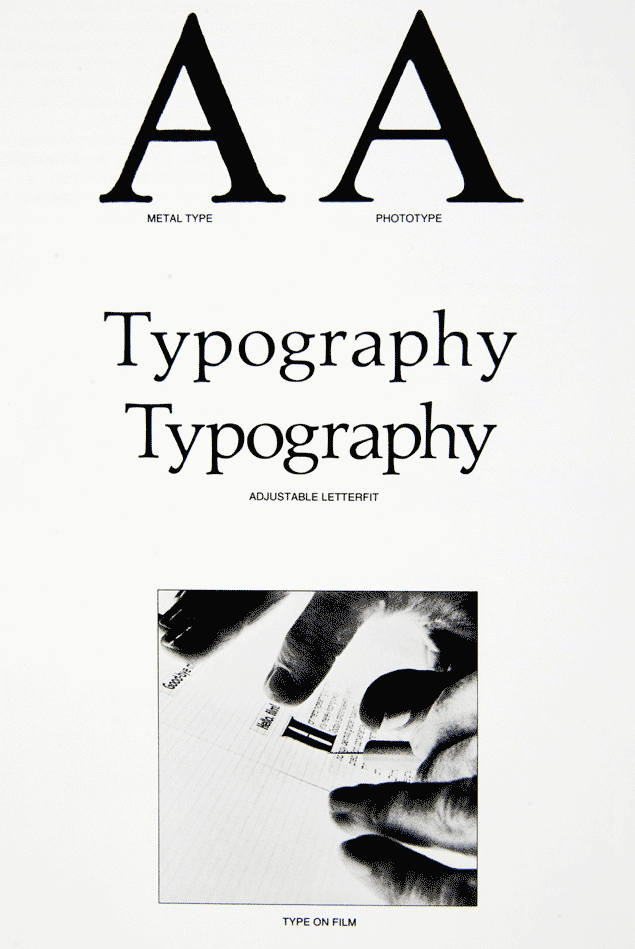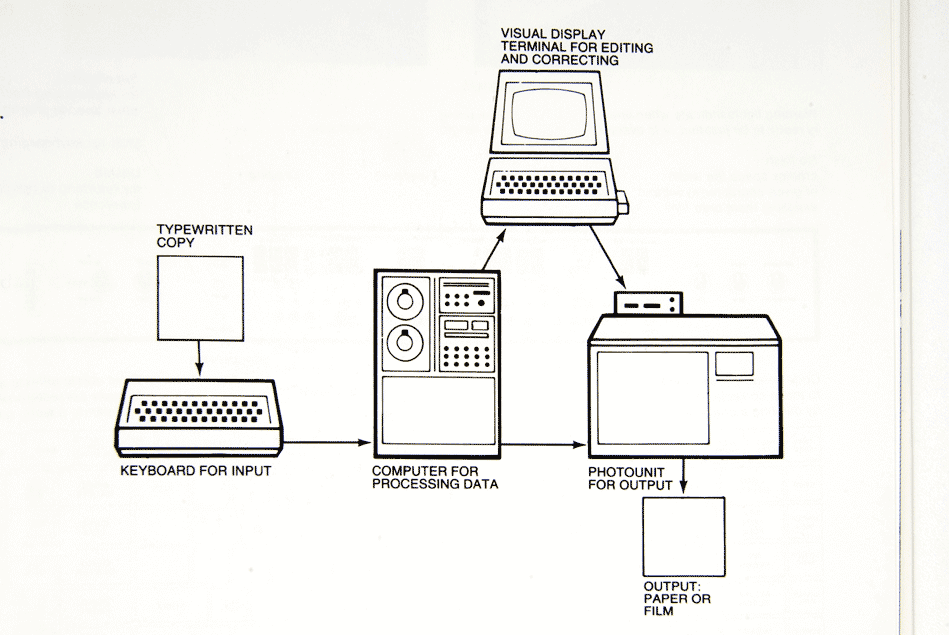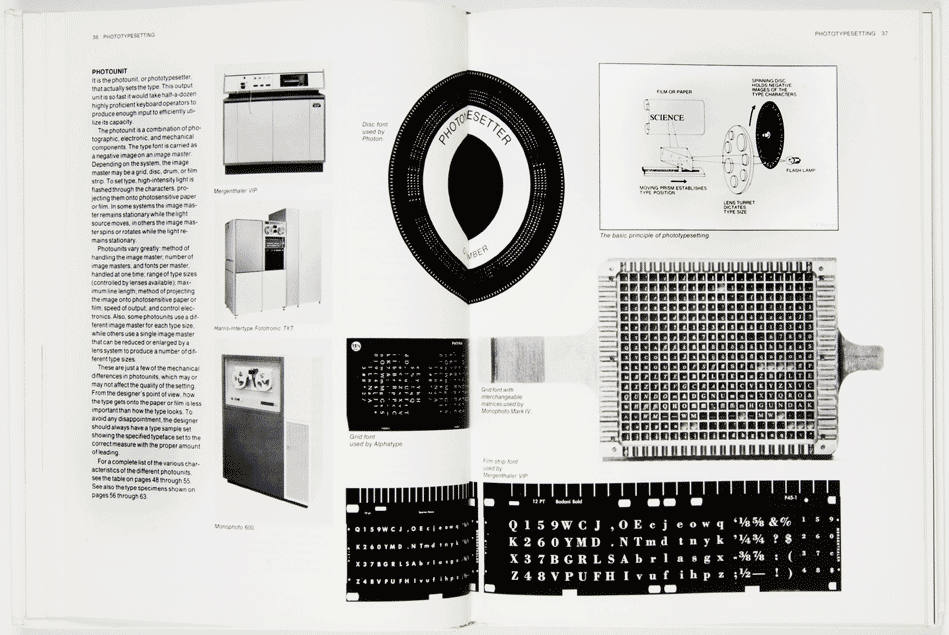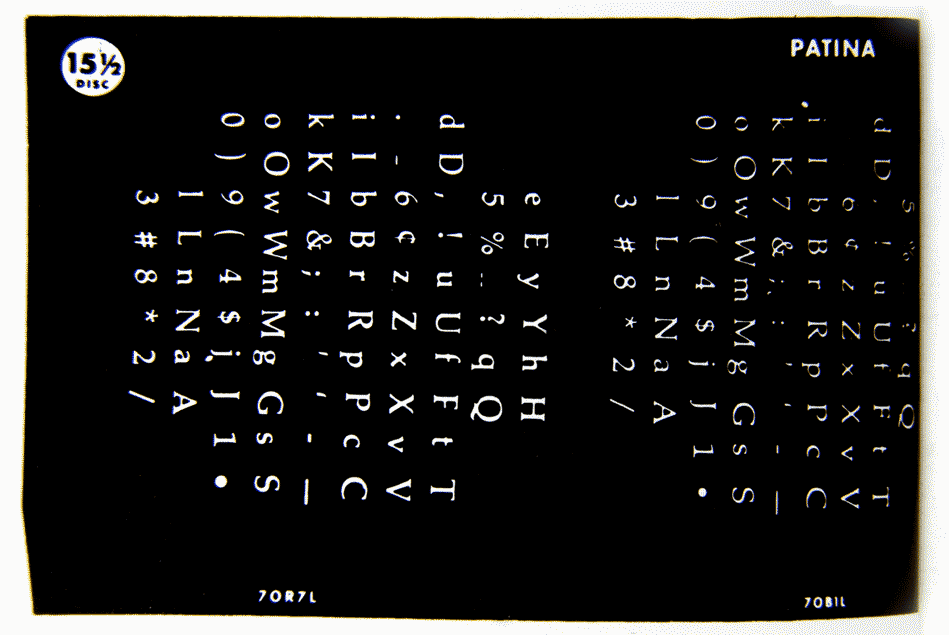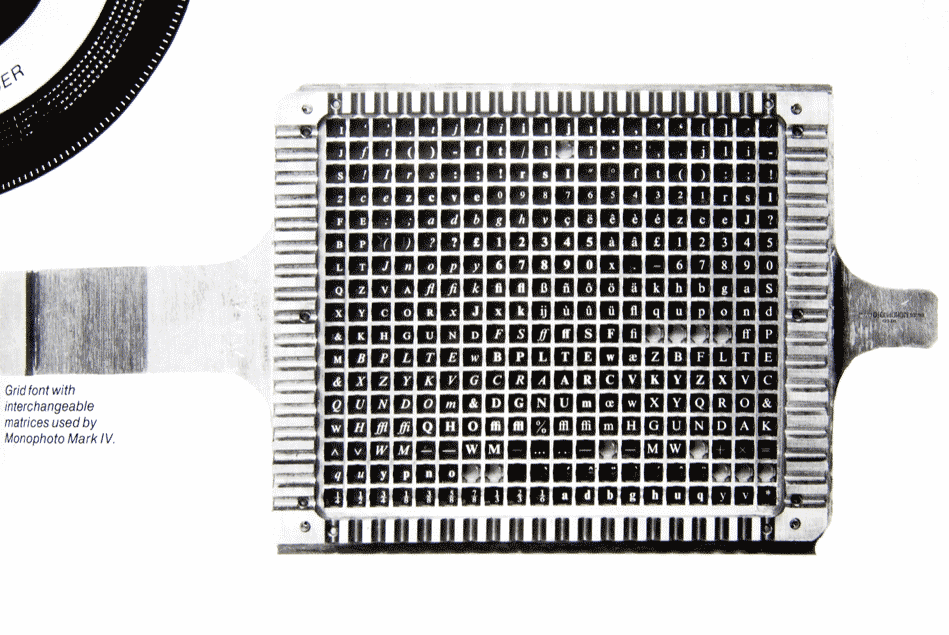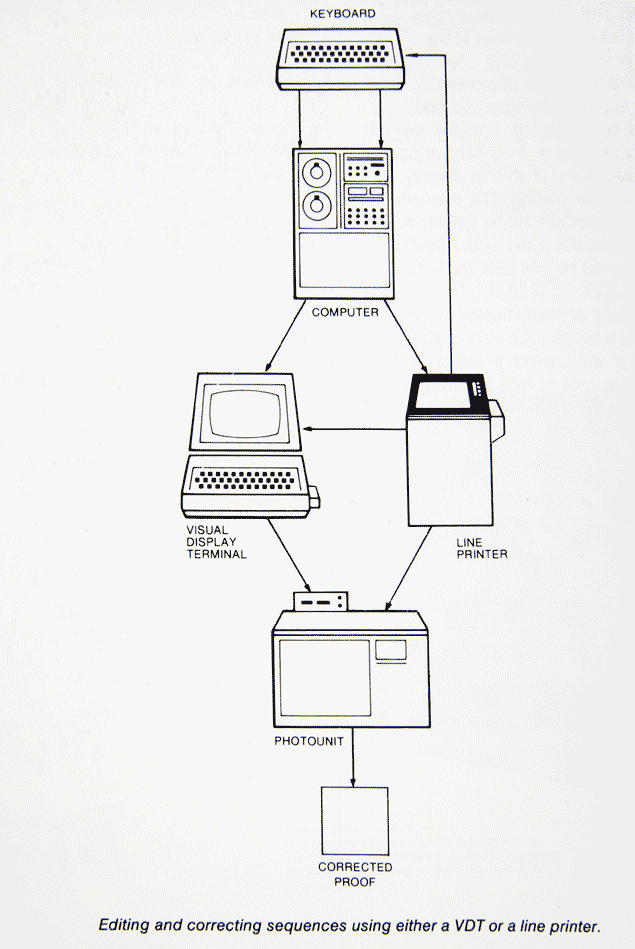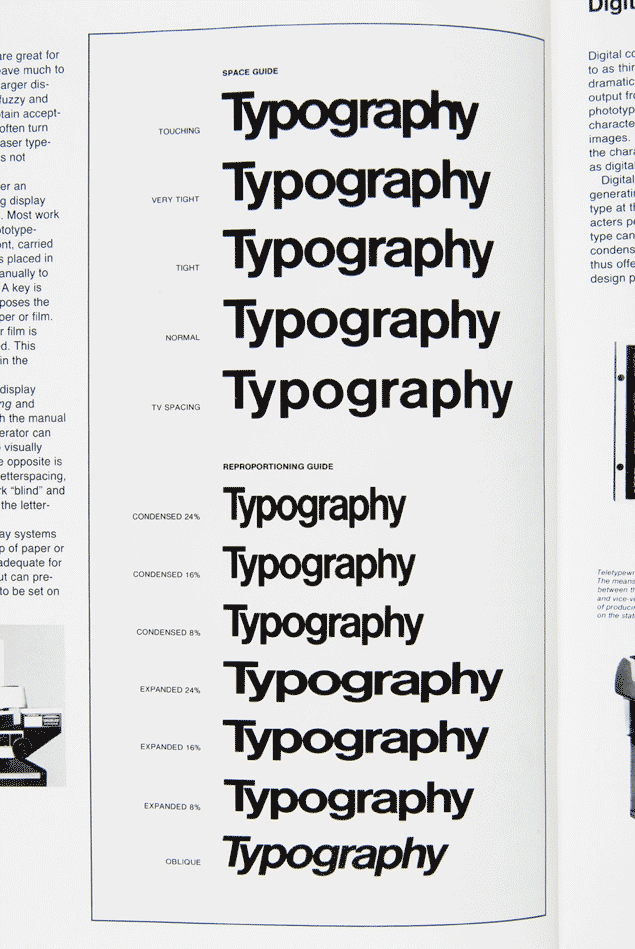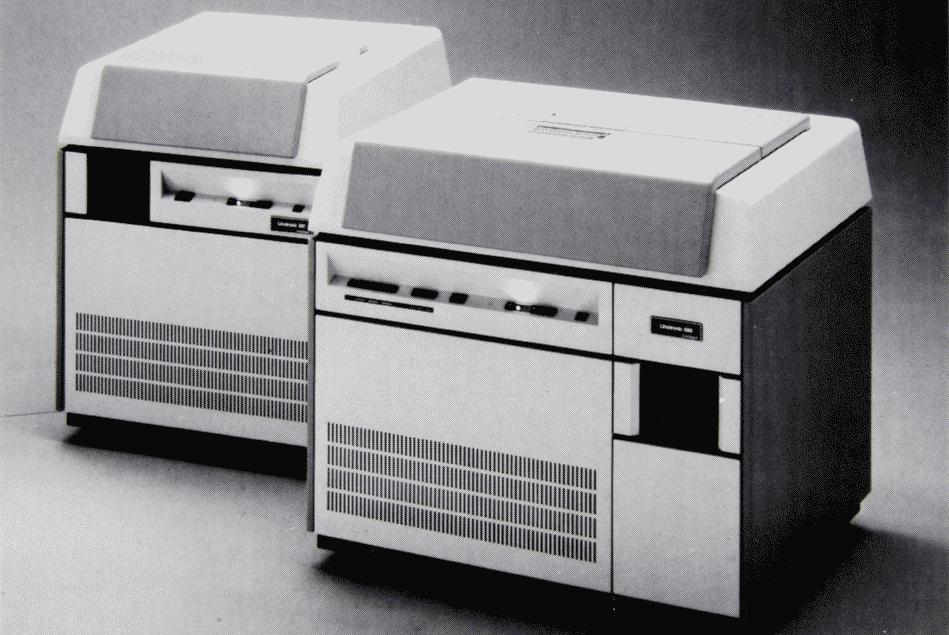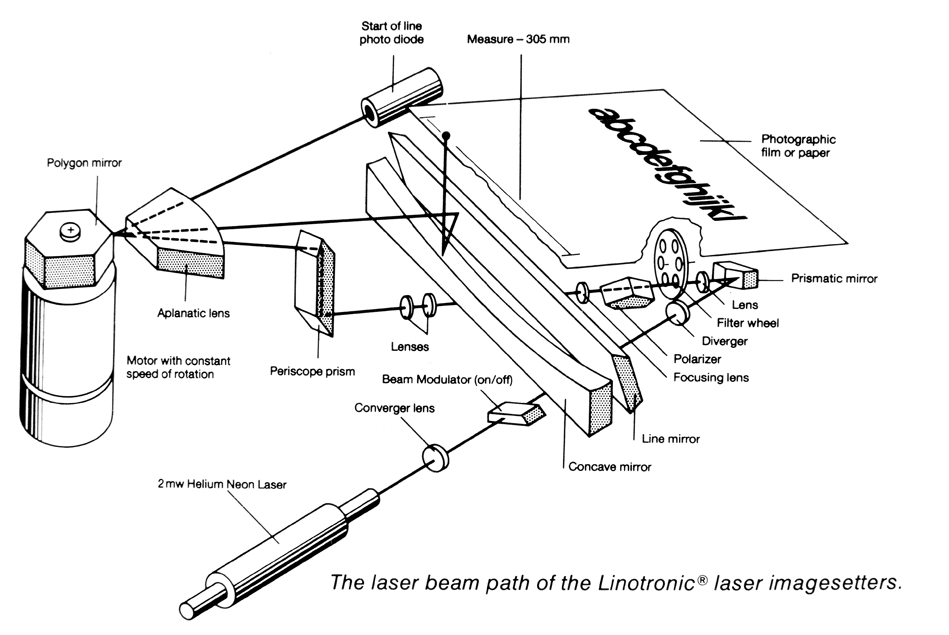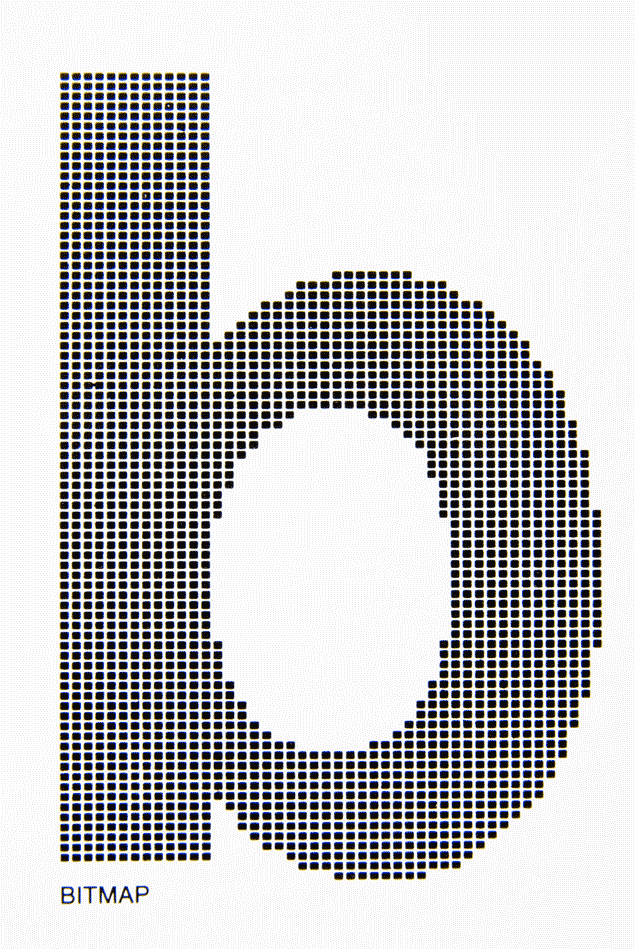
Production graphique pour les graphistes et designers | La typographie: l’ère de la photocomposition
Sous le numéro ISBN 0-8230-4416-5, l’éditeur Watson Guptill Publications a réédité l’ouvrage de James Craig en 1990. Il s’agit de la seconde édition d’une somme qui fut mis en librairie la première fois en 1974. Cet ouvrage n’a pris que quelques rides inhérents aux évolutions technologiques des quinze dernières années. Autrement dit il m’appartient d’y ajouter prochainement deux-trois reportages photo réalisés dans un atelier «pre-press» des plus modernes ainsi que dans une imprimerie qui travaille comme la plupart en DTP, direct to plate, en flux pdf de production.
IBM Selectric MT/ST (en haut) et Smith Corona PWP100 personnal word processor
il faut cliquer sur l’image pour constater la différence de qualité entre une lettre «frappé» par le plomb et une lettre «insolée» par une photocomposeuse.
montage sur film d’une lettrine photographiée avec du texte photocomposée. Le montage effectuée, il est ensuite contretypé en négatif avec un filmprocess orthochromatique (insensible à la lumière rouge) et tirée en positif après retouches pour être montée dans la forme définitive qui servira à la copie de la plaque offset.
Louis Moyroud au centre et René Higonnet à droite, les inventeurs de la Lumitype en 1949 (première photocomposeuse au monde) chez Deberny et Peignot qui durent vendre leurs brevets à l’américain Photon n’ayant pas réussi à interresser les financiers en France. L’ancètre des machines Compugraphic. C’est précisément la Lumitype qui permit à Adrien Frutiger en complicité avec Ladislas Mandel de réaliser la série incroyable des Univers. Les deux ingénieurs, spécialisés dans la transmission et les relais électromagnétiques travaillaient dans les télécomunications de l’époque.
une photocomposeuse également. L’intertype photosetter, où vous retrouvez la structure de fonctionnement des linotypes sauf que les matrices cette fois ne servent plus à couler les lettres en plomb mais à insoler un film, réceptacle du texte.
Fini le saturnisme.
un schéma de photocomposeuse de deuxième génération. Ce qui en fait la particularité, c’est la division des machines. Clavier et enregistrement sur computer des codes d’un côté, et flashage-photocomposition de l’autre. Sorties sur film ou papier.
clavier de photocomposition «enrichi». Le compositeur a accès à toutes les spécifications typographiques sur le clavier. Espaces, entrées, signes de ponctuation typographiques etc. Il fallait en passer par une formation de typographe pour pouvoir accéder à des codes qui étaient abstraits pour les non-initiés. Plus tard on inventa des claviers de saisies dits «au kilomètre» qui permit d’accélérer le processus de saisie, au détriment du contrôle de la qualité des césures, de fins de lignes et du gris typographique.
les interfaces de saisie: bandes perforées, casettes, floppy disques, transmission directe, du clavier à l’ordinateur
les systèmes Monophoto et Harris Intertype. Où l’on voit dans le cas de Monotype les difficultés de sortir d’une culture. La Matrice de la Monophoto était basée rigoureusement sur celle de la Monotype Plomb. Les inventions avancaient très lentement à cette époque pour la raison suivante: les lettres, de plomb sont devenues de lumière (d’où l’expression de composition froide), mais elles étaient physiques. Des négatifs qui laissaient passer la lumière seon des programmes stroboscopiques qui tenaient compte du choix de la lettre au clavier (même si transmis par une bande perforée) pour commander à la Matrice de se trouver à tel endroit et à une lumière au xénon de se déclencher un milliseconde pour venir insoler cette lettre sur un film sensible. Problèmes posées, inerties mécaniques, précision des déclenchements de lumière, et stabilité des supports typo et film réceptacle. Les deux systèmes ci-dessus expriment deux tendances lourdes. D’un coté les matrices carrées (dont Berthold, Alphatype furent friands) et de l’autre les matrices circulaires qui permettaient de diminuer les prbs d’inertie mécaniques mais augmentaient les prbs de sychronisme d’un flashage «à la volée».
matrice d’Alphatype, société située à Chicago qui fut longtemps considéré en Amérique du Nord comme l’équivalent en qualité irréprochable des machines Berthold en Europe. Sauf qu’Alphatype ne voualit pas payer des droits aux créateurs des caractères, ici le PATINA illustre le piratage en règle du Palatino d’Hermann Zapf. Ce type de comportement était la conséquence d’une loi américaine sur le copyright qui ne protégeait pas les dessins mais seulement le nom (trademark) des caractères d’imprimerie.
Monophoto 600
Harris-Intertype Fototronic TXT
Mergenthaler VIP
bande Matrice typographique pour la Mergenthaler VIP